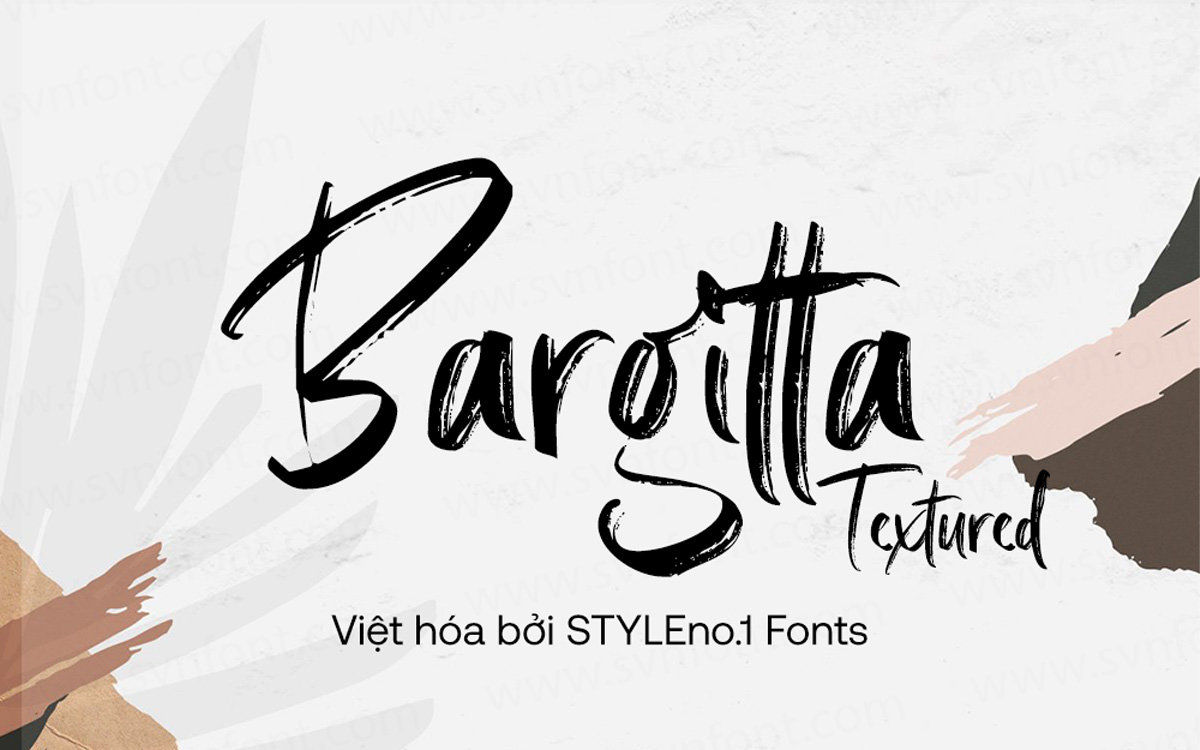
Font chữ viết tay, chữ ký mềm mại cho thiệp cưới, đám cưới SVN Bargitta
SVN Bargitta là bộ font chữ viết tay Việt hóa mang phong cách chữ ký mềm mại, vô cùng sang trọng và thanh lịch dành riêng cho các thiết kế thiệp cưới, đám cưới hiện đại. Với từng đường nét uốn lượn bay bổng và phóng khoáng, font chữ này giúp nâng tầm giá trị thẩm mỹ, mang đến dấu ấn cá nhân độc đáo cho ngày trọng đại của các cặp đôi. Nếu bạn đang tìm kiếm một font chữ vừa thể hiện sự lãng mạn vừa giữ được độ chỉn chu nghệ thuật, SVN Bargitta chính là sự lựa chọn hoàn hảo nhất.
Font Chữ Viết Tay, Chữ Ký Mềm Mại Cho Thiệp Cưới, Đám Cưới SVN Bargitta – Đột Phá Thẩm Mỹ Cho Thiết Kế Sang Trọng
Nét chữ uốn lượn tự nhiên, đậm chất chữ ký nghệ thuật
SVN Bargitta sở hữu phong cách calligraphy đương đại với những đường nét thanh đậm được trau chuốt vô cùng tỉ mỉ. Từng ký tự được tạo hình tự nhiên như dòng mực chảy ra từ ngòi bút máy cao cấp, mang lại cảm giác phóng khoáng nhưng vô cùng tinh tế. Điểm đặc biệt của font chữ này chính là khả năng mô phỏng hoàn hảo nét chữ ký tay cá nhân, giúp cho tên của cô dâu, chú rể hay các dòng tiêu đề trên thiệp cưới trở nên nổi bật, tràn đầy cảm xúc và ghi dấu ấn sâu sắc trong lòng khách mời.
Việt hóa hoàn thiện, chuẩn xác từng ký tự Unicode
Một trong những vấn đề lớn nhất khi sử dụng các bộ font chữ viết tay nước ngoài là lỗi dấu tiếng Việt bị lệch, bị mất nét hoặc thiếu cân đối. SVN Bargitta đã được đội ngũ thiết kế Việt hóa trọn bộ với sự chuẩn xác tuyệt đối theo chuẩn Unicode. Mọi dấu câu như hỏi, ngã, sắc, huyền, nặng cùng các chữ cái đặc trưng (ă, â, đ, ê, ô, ơ, ư) đều được xử lý tinh tế, đảm bảo không làm phá vỡ cấu trúc tổng thể của nét chữ. Nhờ đó, bạn có thể tự tin sáng tạo các đoạn văn bản tiếng Việt mượt mà và thẩm mỹ nhất.
Bộ ký tự thay thế (Swashes & Ligatures) phong phú và đa dạng
SVN Bargitta tích hợp tính năng OpenType thông minh với hàng loạt ký tự thay thế (Alternate Characters), nét nối liền mạch (Ligatures) cùng các nét uốn lượn nghệ thuật (Swashes) kéo dài ở đầu và cuối từ. Điều này cho phép các nhà thiết kế tự do biến tấu, kết hợp các ký tự để tạo nên những bộ chữ ký độc bản, không đụng hàng. Sự biến hóa linh hoạt của các nét móc, nét bay giúp bố cục thiết kế trở nên uyển chuyển, giàu tính nghệ thuật và thu hút ánh nhìn ngay từ lần đầu tiên.</p>
Tính ứng dụng cao trong nhiều sản phẩm thiết kế cưới và truyền thông
Không chỉ giới hạn trong việc thiết kế thiệp cưới hay thiệp mời đám cưới, SVN Bargitta còn tỏ ra cực kỳ đa năng trong nhiều lĩnh vực sáng tạo khác nhau. Bộ font chữ ký mềm mại này vô cùng thích hợp để thiết kế logo thương hiệu thời trang, mỹ phẩm, spa, nhận diện thương hiệu cao cấp, làm bìa album ảnh cưới, làm watermark bảo vệ bản quyền hình ảnh, hay trang trí các ấn phẩm truyền thông, banner quảng cáo và hình ảnh đăng tải trên các nền tảng mạng xã hội.
Được tối ưu hóa sắc nét cho cả in ấn và hiển thị kỹ thuật số
Cho dù được ứng dụng trên các chất liệu in ấn cao cấp như giấy mỹ thuật gân, giấy ép kim, giấy can trong suốt hay hiển thị trên màn hình thiết bị di động (thiệp cưới online, website, slide trình chiếu), SVN Bargitta vẫn duy trì độ rõ nét hoàn hảo. Đường nét của font chữ không bị đứt gãy hay nhòe mờ khi phóng to hoặc thu nhỏ, giúp giữ trọn vẹn chất lượng nghệ thuật của bản thiết kế dù ở bất kỳ định dạng xuất bản nào.
Tại Sao SVN Bargitta Là Sự Lựa Chọn Hàng Đầu Cho Thiệp Cưới Đám Cưới?
Trong xu hướng thiết kế thiệp cưới hiện đại, sự tối giản kết hợp với yếu tố điểm nhấn nghệ thuật đang chiếm ưu thế. Tấm thiệp cưới không đơn thuần là công cụ thông tin mà còn thể hiện gu thẩm mỹ và tình yêu của đôi uyên ương. SVN Bargitta đáp ứng trọn vẹn các yêu cầu này nhờ vào những ưu điểm vượt trội:</p>
• Tạo ấn tượng thị giác mạnh mẽ: Vẻ đẹp bay bổng của dòng chữ ký giúp thiệp cưới trở nên sang trọng, thoát khỏi vẻ khô cứng của các font chữ truyền thống.
• Dễ dàng phối hợp font chữ: SVN Bargitta kết hợp cực kỳ ăn ý với các font chữ không chân (Sans-Serif) hiện đại hoặc font có chân (Serif) cổ điển, tạo nên sự cân bằng hoàn hảo giữa nét uốn lượn nghệ thuật và tính dễ đọc của thông tin.
• Tiết kiệm thời gian sáng tạo: Thay vì phải vẽ tay thủ công từng nét chữ calligraphy phức tạp, bạn có thể tạo ra các sản phẩm hoàn mỹ chỉ trong vài thao tác gõ phím.
Hướng Dẫn Sử Dụng Font SVN Bargitta Để Đạt Hiệu Quả Thẩm Mỹ Cao Nhất
Để tận dụng tối đa vẻ đẹp của SVN Bargitta trong các sản phẩm thực tế, bạn có thể áp dụng những bí quyết thiết kế sau:
1. Tập trung vào các chi tiết chính: Sử dụng SVN Bargitta cho tên chú rể – cô dâu, tiêu đề “Thiệp Mời”, hoặc các câu trích dẫn ngắn. Không nên dùng cho các đoạn văn bản dài chứa địa điểm, thời gian để tránh gây rắc rối thị giác cho người đọc.
2. Lựa chọn màu sắc tinh tế: Font chữ này thể hiện vẻ đẹp tuyệt vời nhất khi kết hợp với các hiệu ứng ép kim (foil stamping) màu vàng gold, hồng rose gold, hoặc dùng các tông màu tối như đen tuyền, xanh navy trên nền giấy sáng màu.